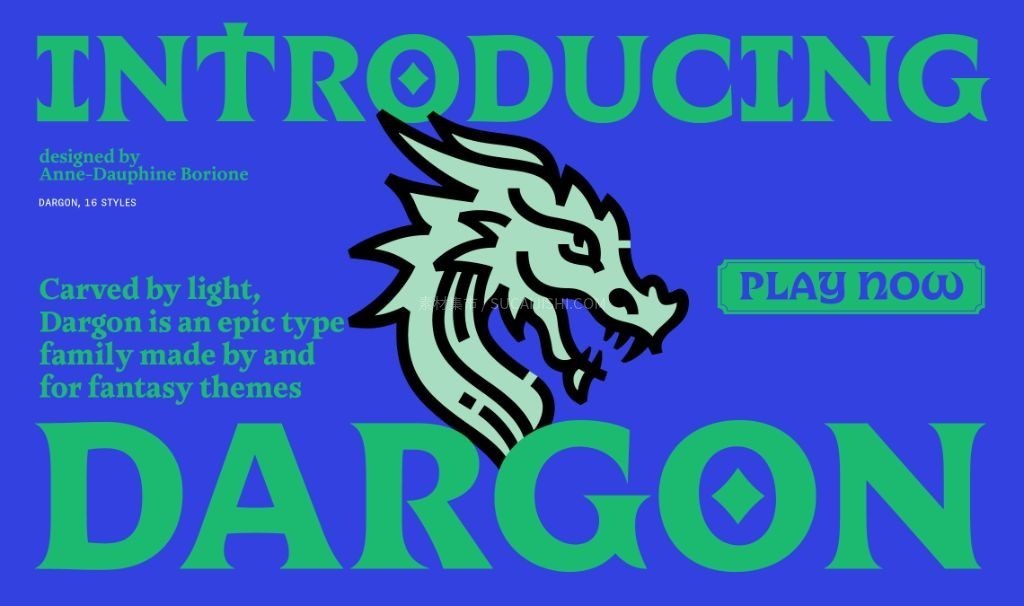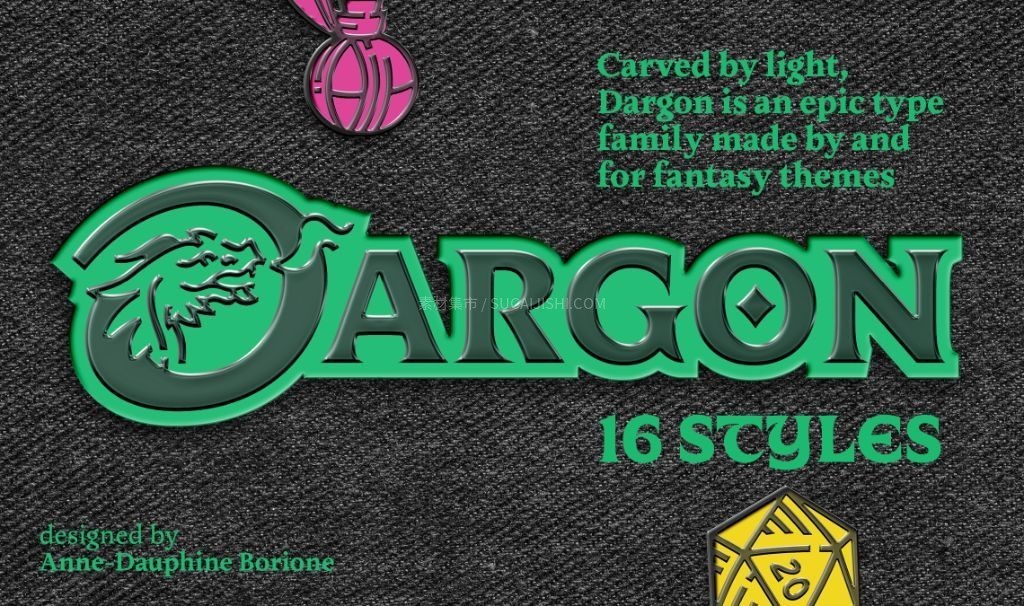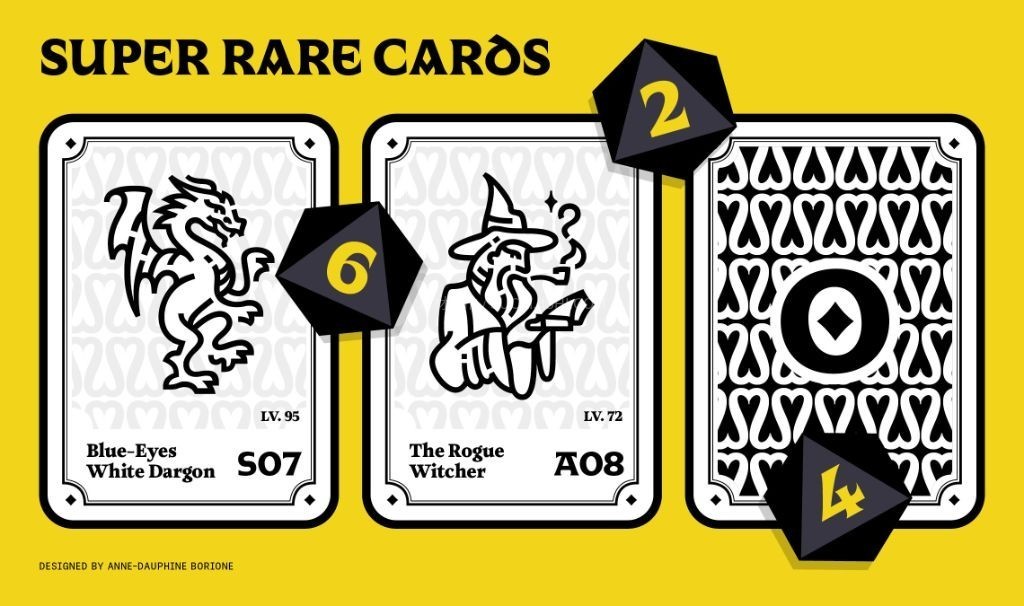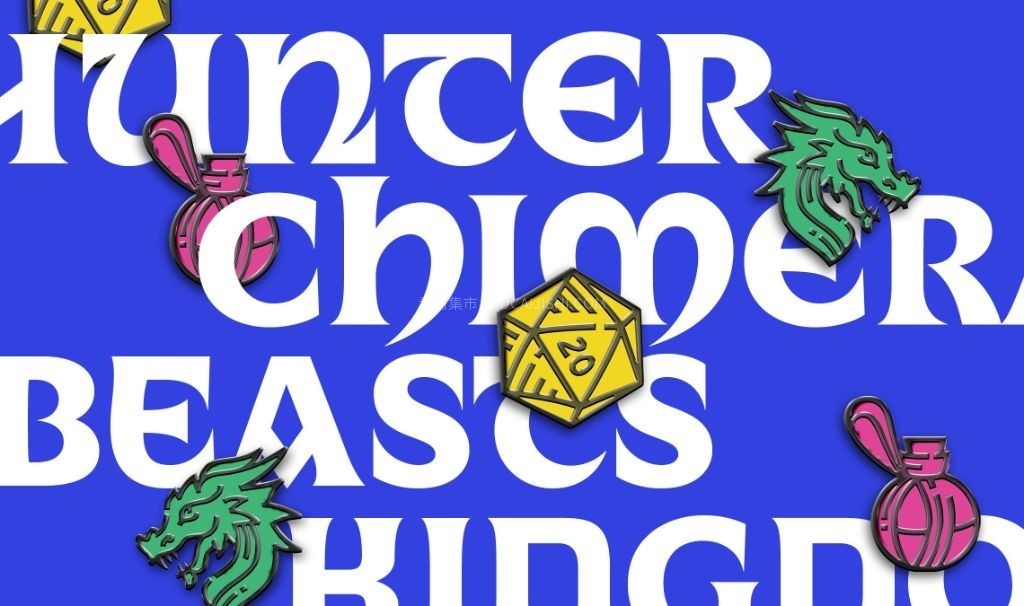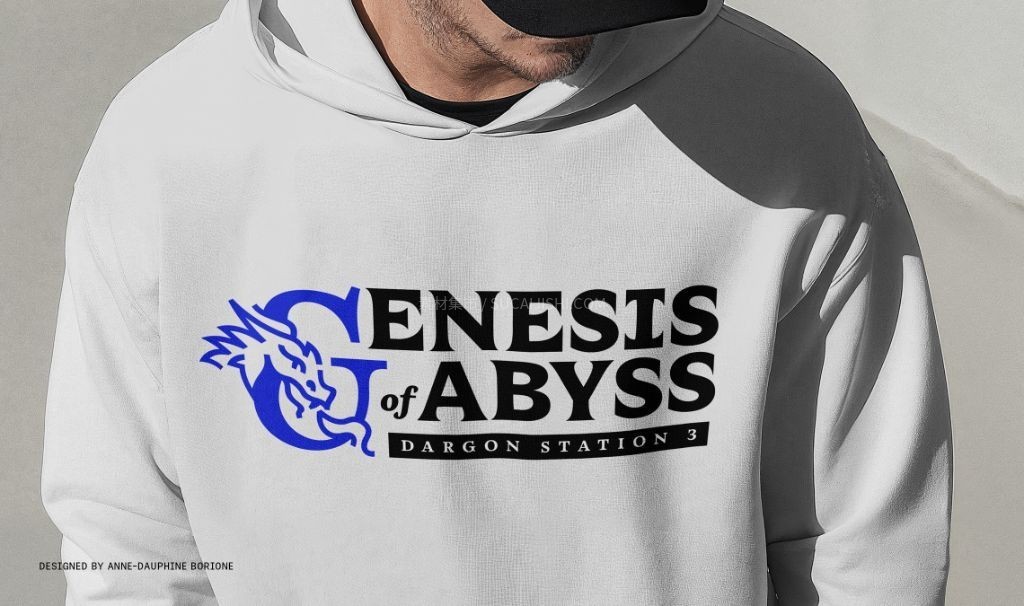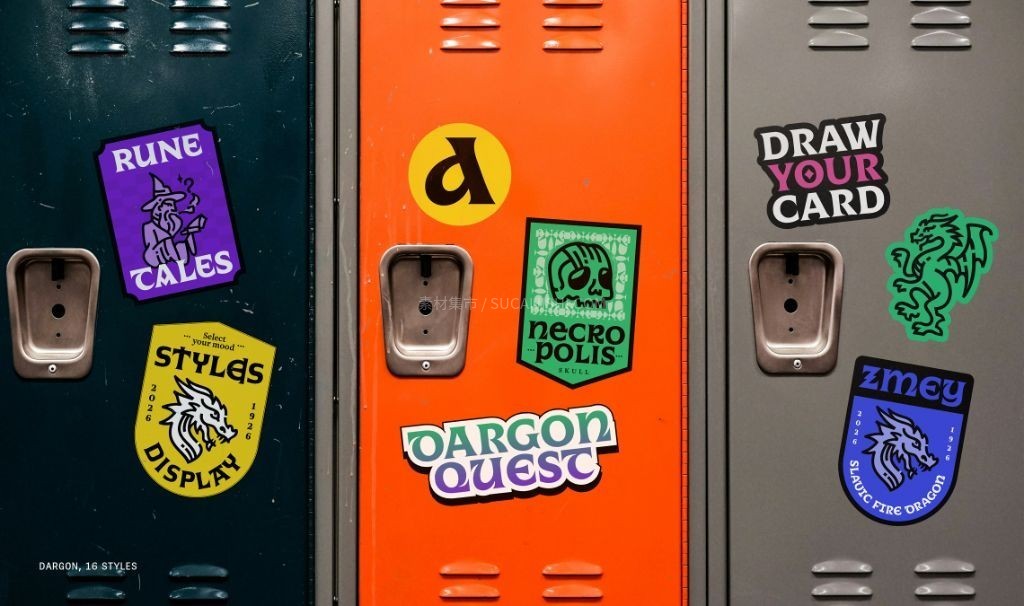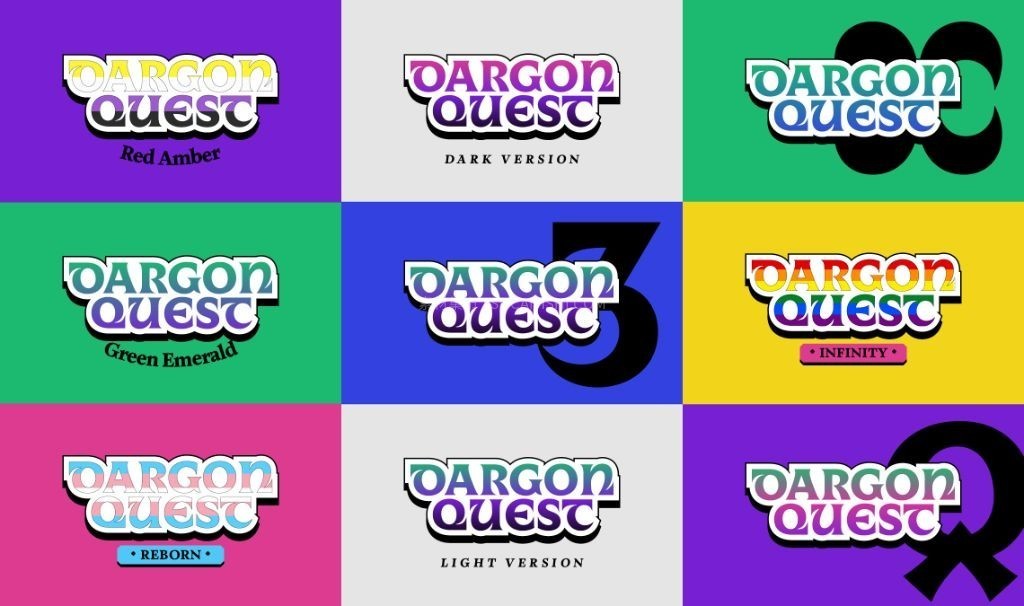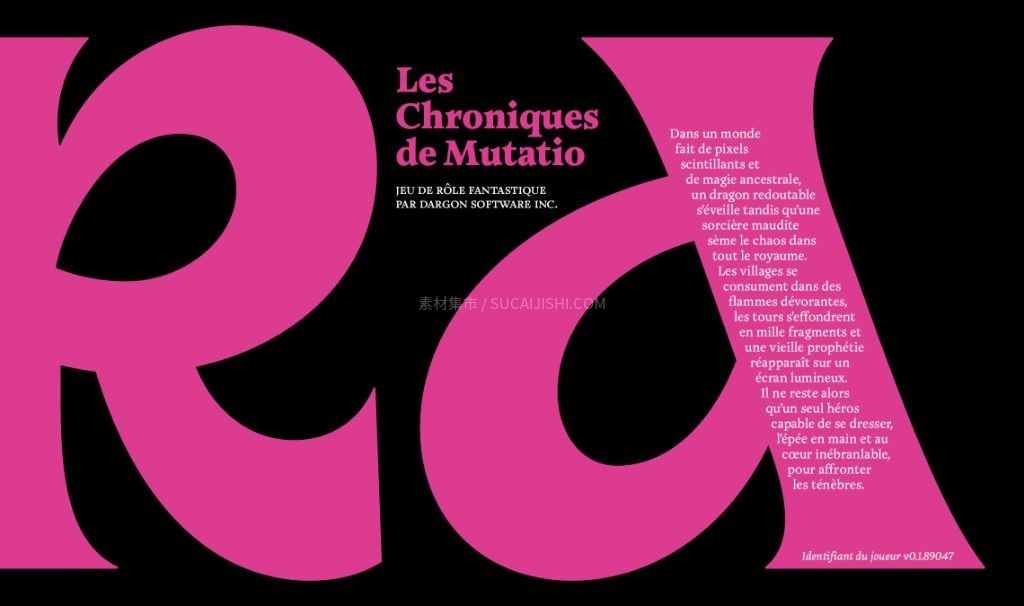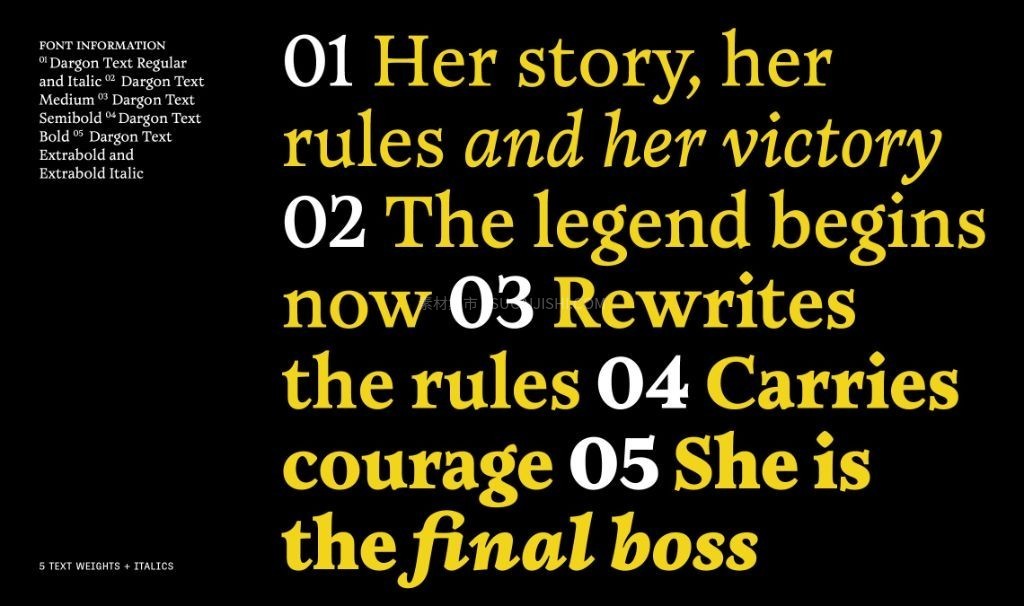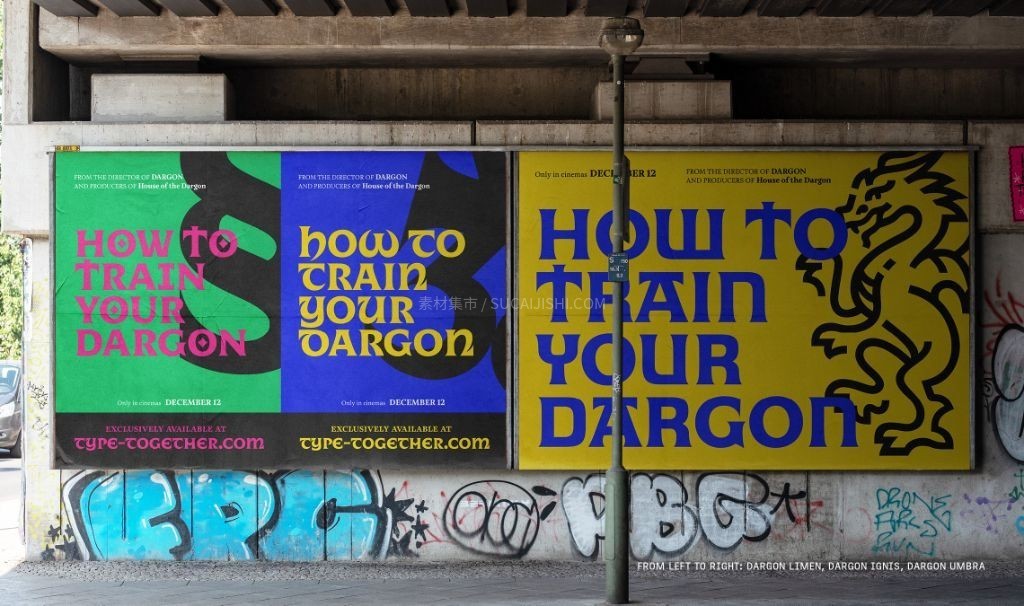
Dargon 奇幻中世纪字体(16种样式+2款可变字体)
这套名为 Dargon 的史诗级奇幻字体家族,绝对是你开启视觉冒险的完美伴侣!它荣获了2024年Gerard Unger奖学金,巧妙地将公元4至8世纪的中世纪安色尔体书法与未来主义美学相融合。全套包含5种正文字重及斜体,外加6款以“魔法咒语”命名的特色标题字。无论是需要在极其有限的RPG卡牌空间里排版海量信息,还是在游戏UI和书籍封面中营造沉浸式的魔法氛围,Dargon 都能轻松驾驭,完美平衡阅读清晰度与纯粹的奇幻故事感。